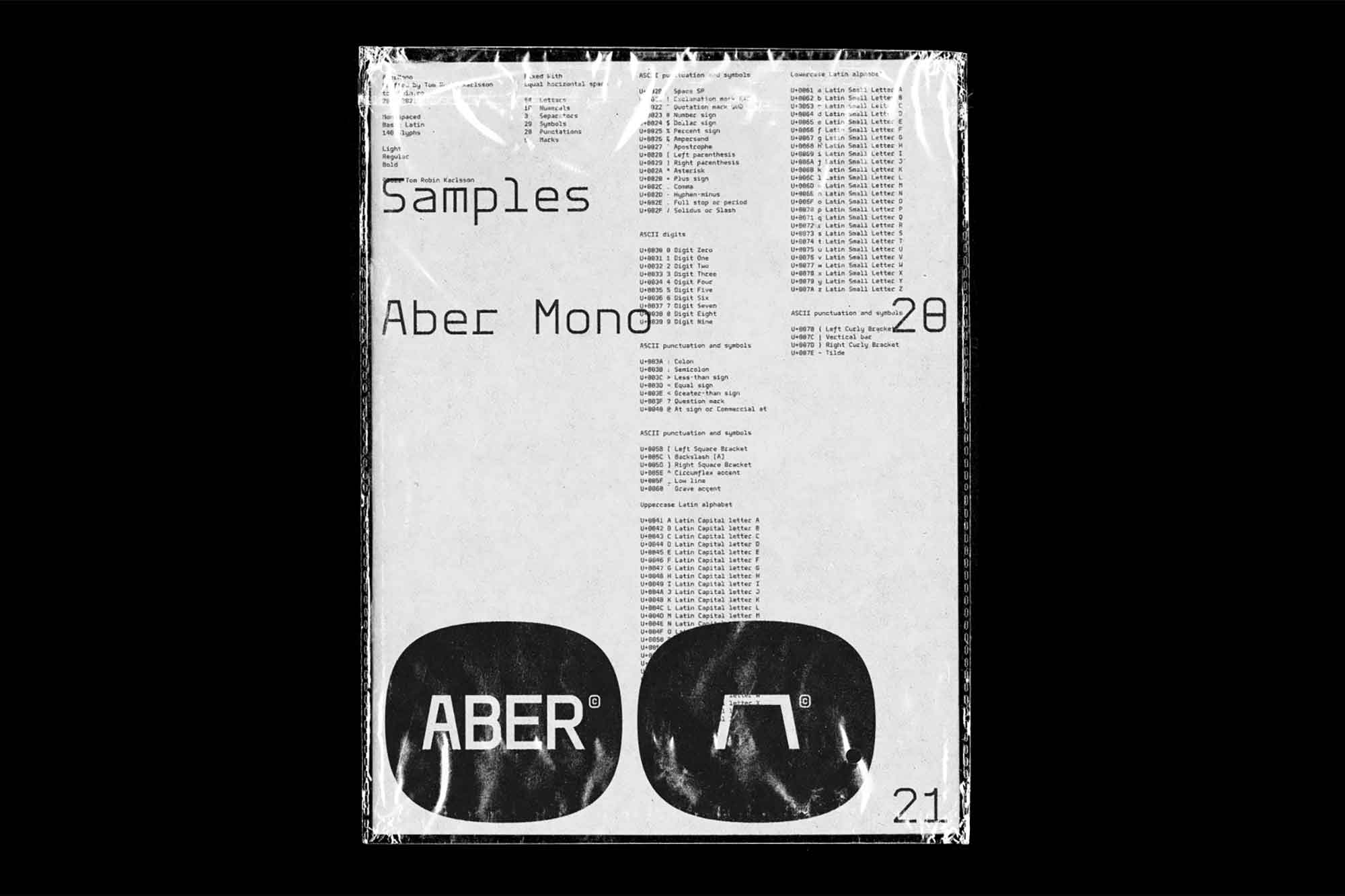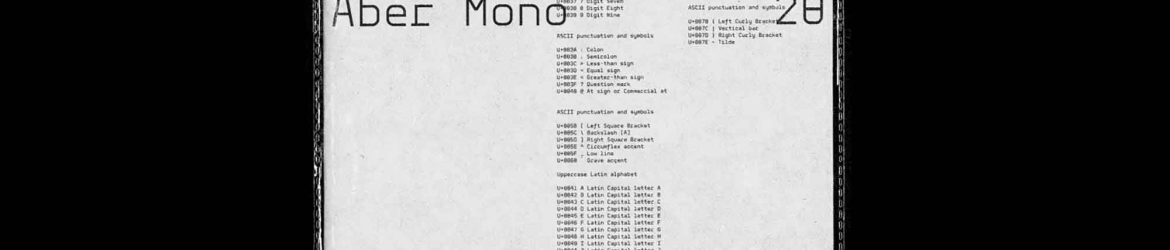
Aber Mono é uma fonte monoespaciada versátil que incorpora uma construção geométrica, um elemento que valoriza a contraste entre ângulos agudos e suaves. Esta fonte de graça inclui suporte multilíngue e é disponível em três pesos: leve, regular e bold. Este recurso gráfico não impõe limites ao seu uso, seja em conjunto com quaisquer outras fontes. Possui inúmeras possibilidades para uso em cabeçalhos, títulos, embalagens, posters, designs de marca, sites e aplicativos móveis. É perfeito para criar uma aparição minimalista e moderna, o que o torna uma opção perfeita para qualquer projeto gráfico. Seja ele um projeto de marca ou um site de design web, Aber Mono oferece aprimoramento e profissionalismo.